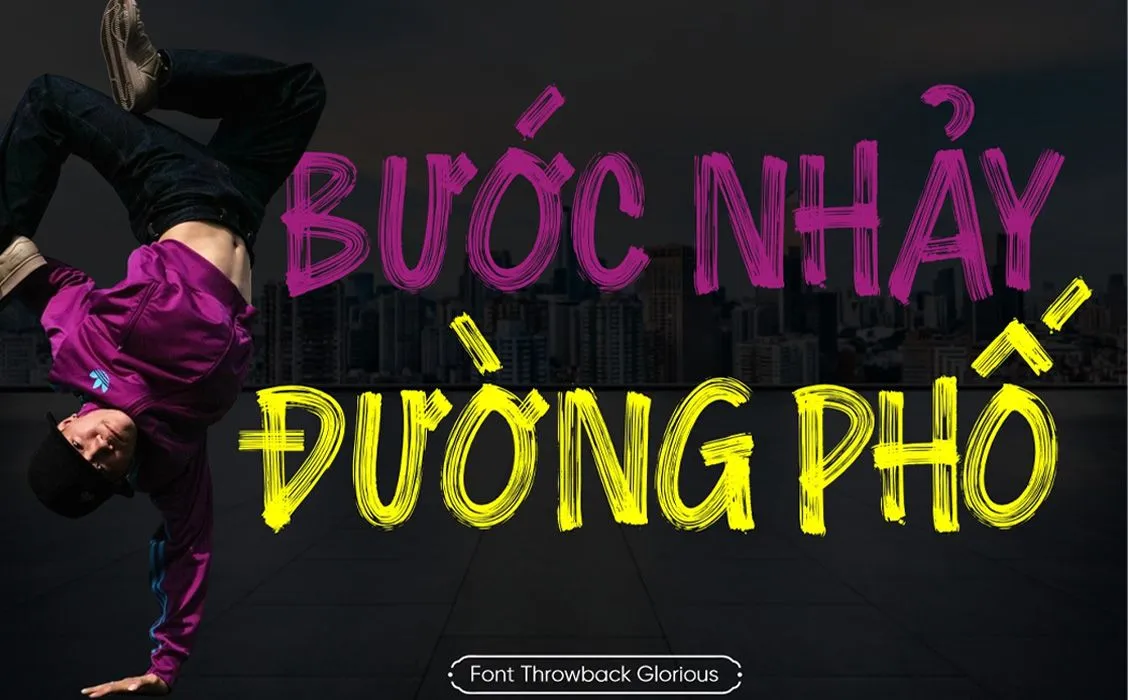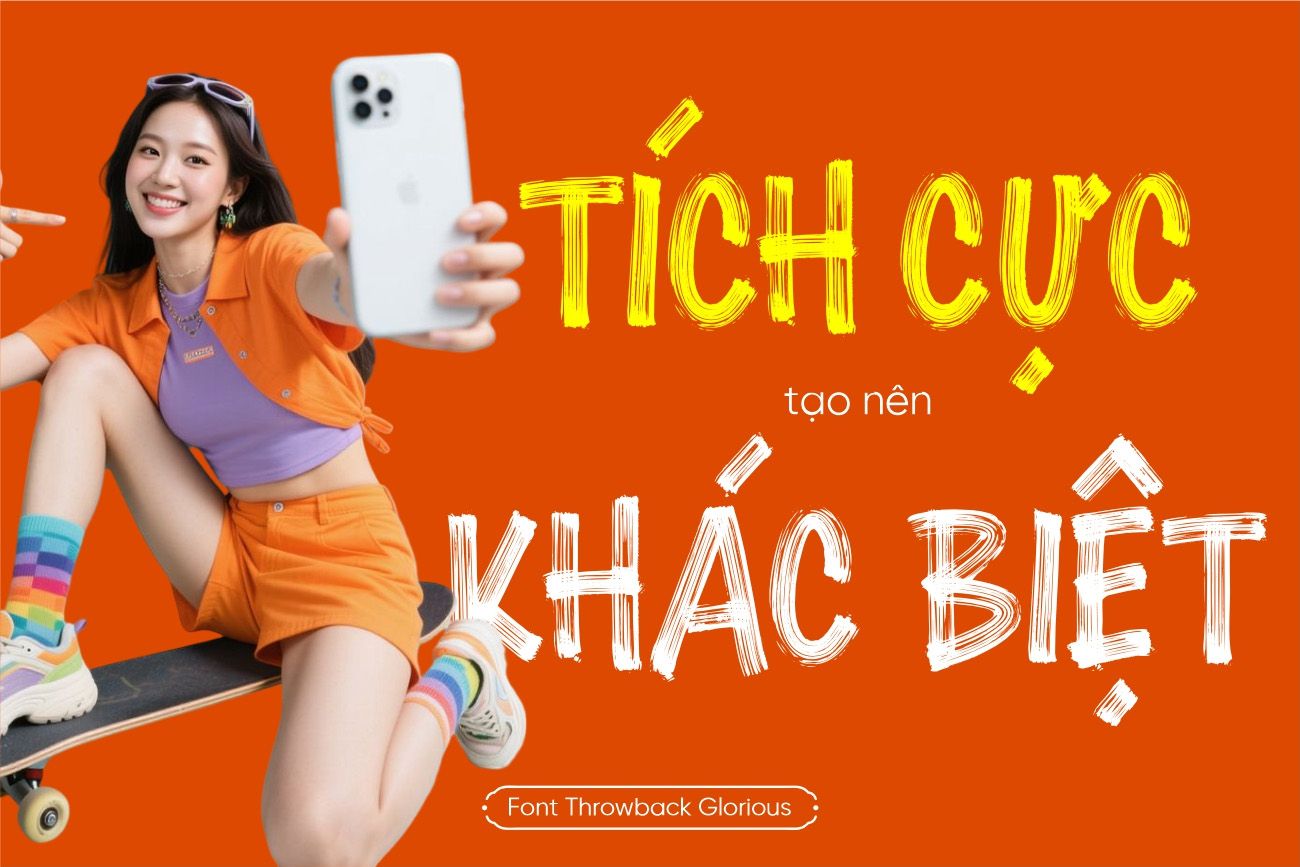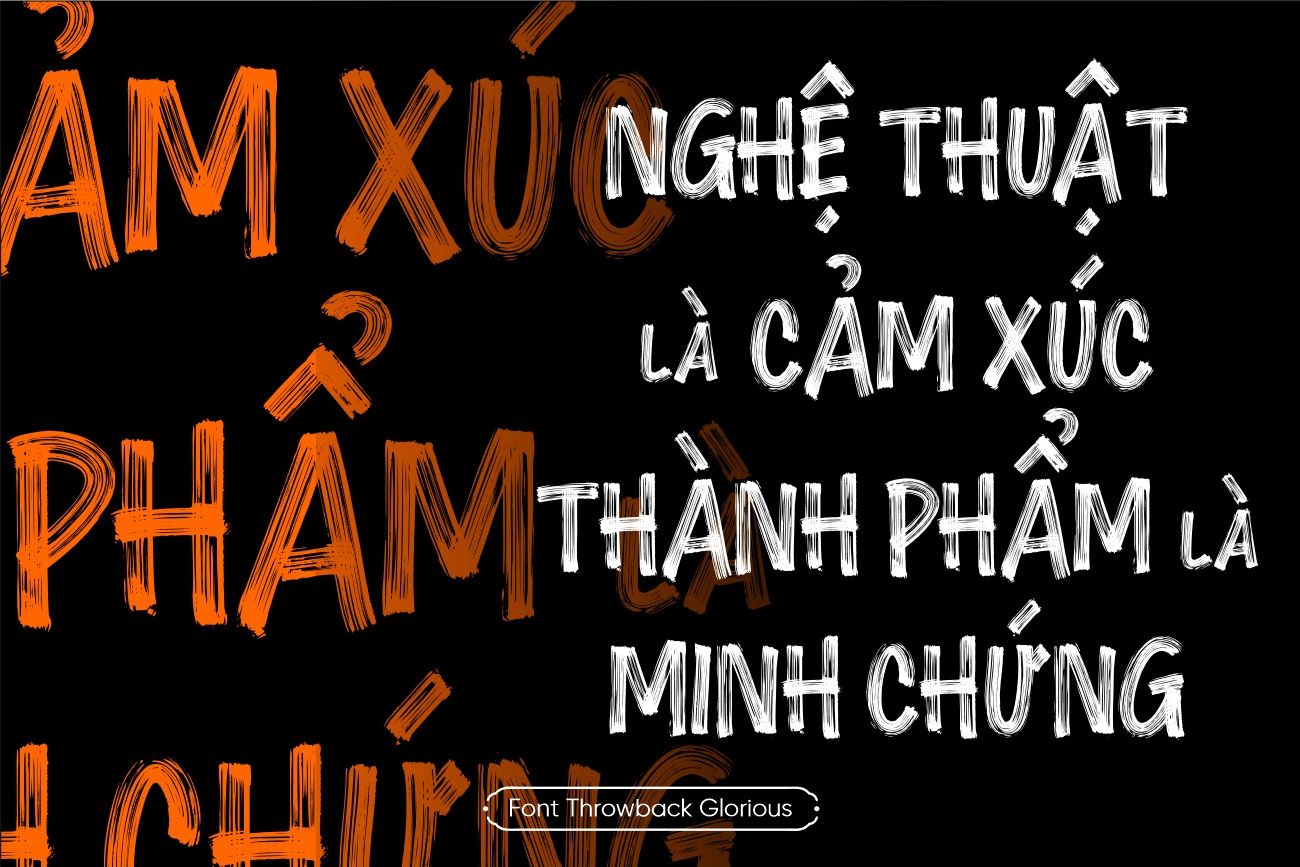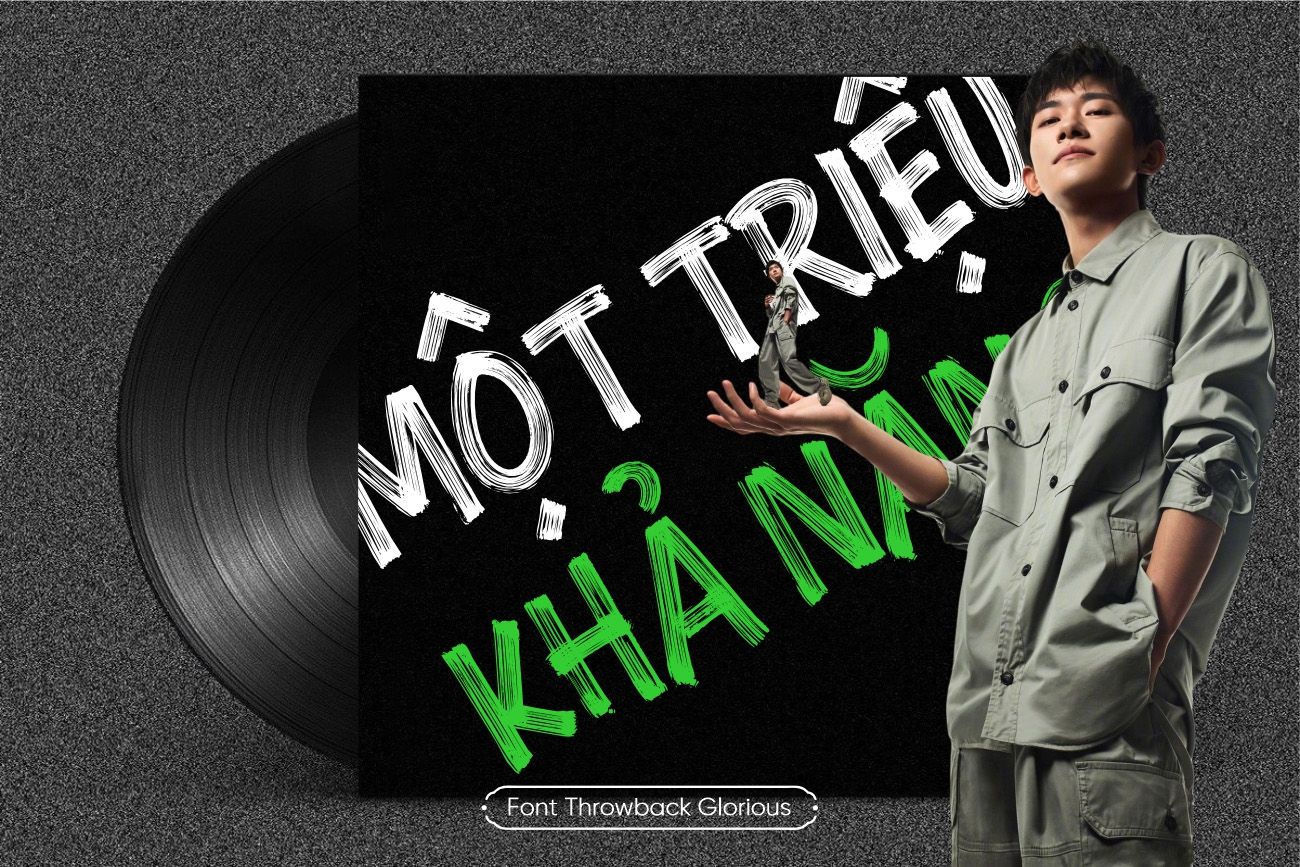
Đánh thức tinh thần tự do và nhịp sống hối hả của đô thị, TH Throwback Glorious Việt hóa là một bản tuyên ngôn đầy năng lượng cho những thiết kế mang phong cách đường phố. Với hiệu ứng cọ vẽ (brush) thô mộc, mỗi nét chữ như được tạo nên từ những nhát sơn xịt đầy ngẫu hứng trên những bức tường graffiti, mang đến một vẻ ngoài vừa bụi bặm, vừa tràn đầy sức sống.
Điểm đặc biệt của TH Throwback Glorious chính là sự chuyển động trong từng cấu trúc chữ. Các vệt lông cọ được giữ lại một cách chân thực, tạo ra chiều sâu và độ rung thị giác mạnh mẽ, lý tưởng để thể hiện hơi thở của văn hóa Hip-hop, Skating hay Underground. Bản Việt hóa đã được tối ưu hóa xuất sắc, giúp các dấu tiếng Việt không chỉ sắc nét mà còn giữ trọn vẹn sự phóng khoáng, không chút gò bó. Đây là lựa chọn hàng đầu cho:
Poster sự kiện thể thao & âm nhạc: Đặc biệt là các giải đấu Street Dance hoặc Rock show.
Thiết kế áo thun & Phụ kiện: Tạo nên phong cách Streetwear cá tính và khác biệt.
Thumbnail YouTube & Branding: Phù hợp cho các vlogger du lịch bụi, thể thao mạo hiểm hoặc review văn hóa đường phố.
Với TH Throwback Glorious, mỗi dòng chữ của bạn không chỉ là nội dung truyền tải, mà còn là nhịp đập của một phong cách sống năng động và phá cách.